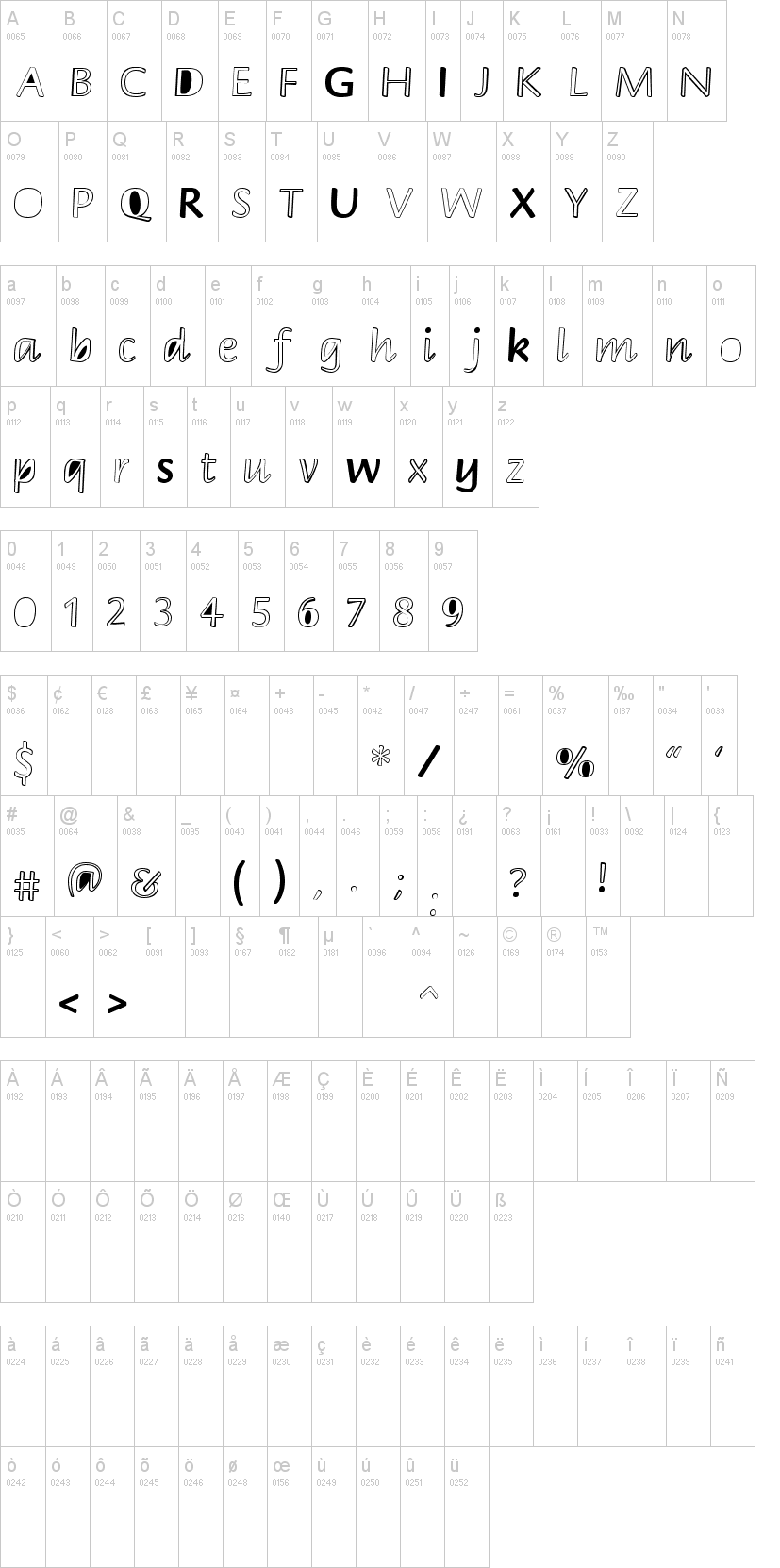
Peekaboo 2
Peekaboo 2 是一款由字体设计师 Nicky Laatz 创作的一款脚本字体,它采用细腻的曲线和折线,拥有优美的笔画,可以创造出温柔可爱的设计感。Peekaboo 2 的特色是它的折线让字体的动感和节奏感更强烈,它的曲线更显柔和,让文字看起来更加舒服。它适用于各种类型的设计,可以在海报、标语、标签、卡片等等中使用。
Peekaboo 2是一款非常不错的手写艺术字体,具有很好的视觉感,适合于文化类的宣传设计、商业类品牌的广告和产品包装设计以及个性化文字排版等较多场景。